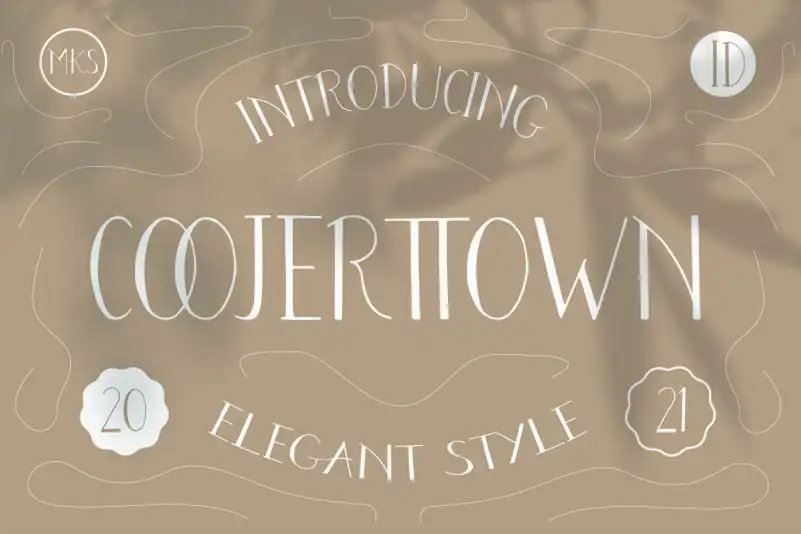
A fonte Coojertown Display é uma elegante fonte estreita projetada para criar designs refinados e sofisticados. Com seu formato compacto cuidadosamente criado, esta fonte permite que designers de gráficos construam layouts arquitetonicamente perfeitos, combinando elegância com utilidade. Ideal para aplicativos como portais online, sites profissionais ou materiais impressos para empresas de alto padrão, Coojertown Display é uma escolha inteligente para quem busca um estilo moderno e sofisticado em sua próxima criação visual.